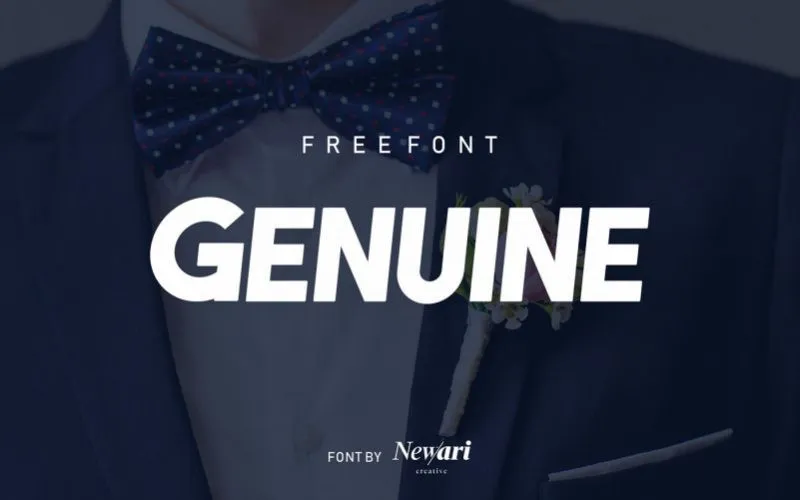
Genuine Sans Font – Download Grátis
Introduzimos a Genuine Sans Font, uma nova opção para designers que buscam elegância ao criar projetos digitais. Este estilo de tipo sans-serif foi desenvolvido com um mix sofisticado de curvas suaves e linhas retas fortes, criando um arquétipo único e ousado. A Honestidade é a inspiração por trás deste design, que busca equilibrar clareza de leitura com uma personalidade distintiva. A combinação desta fonte é perfeita para trabalhos em grandes títulos, logos ou pequenos parágrafos, ajudando você a expressar sua criatividade e habilidades tipográficas. Com uma elegância que vai além do básico, a Genuine Sans Font está idealmente equipada para tornar qualquer projeto mais profissional e sofisticado. Seja em um ambiente de design digital ou impressão, ela se destaca por sua forma minimalista e clara, enquanto mantém seu toque único. Para aqueles em busca de uma fonte com um diferencial estético, a Genuine Sans Font é uma ótima opção. Ela promete não apenas transmitir informações de maneira rápida e fácil de ler, mas também oferecer um design visual que vai alongar seus trabalhos para além do básico.